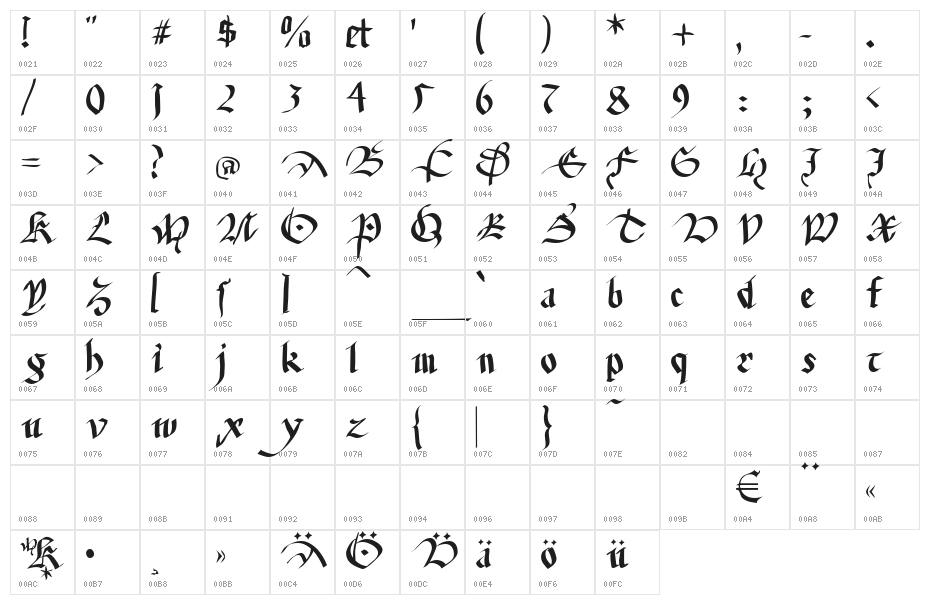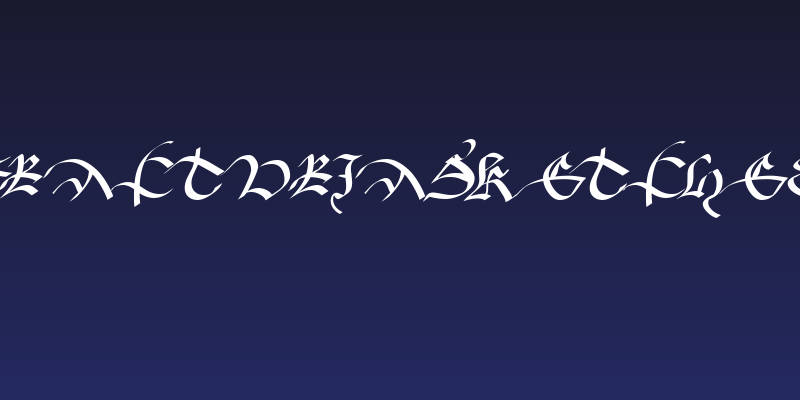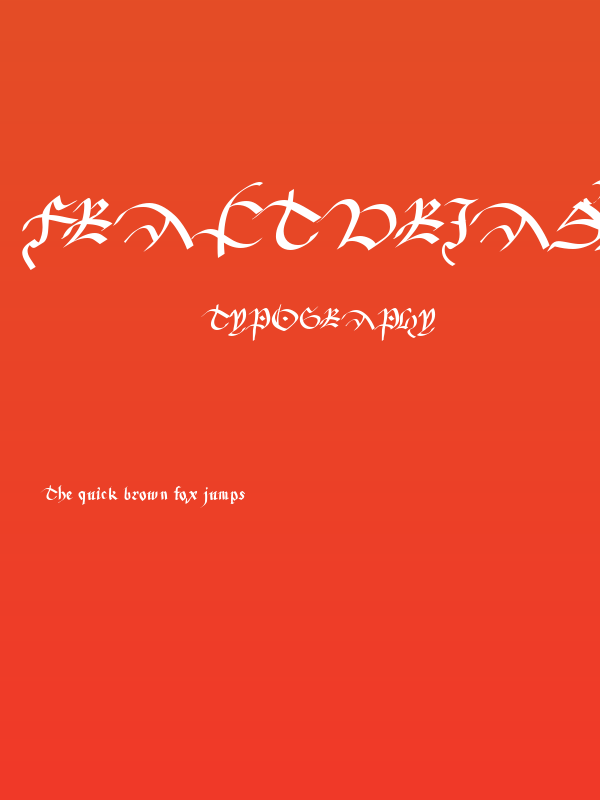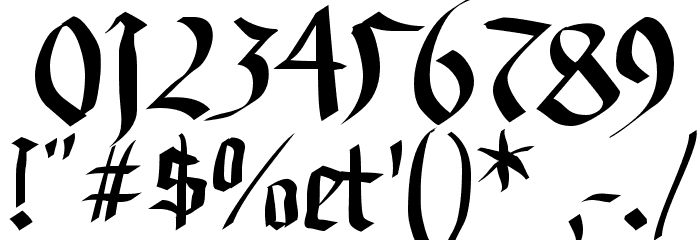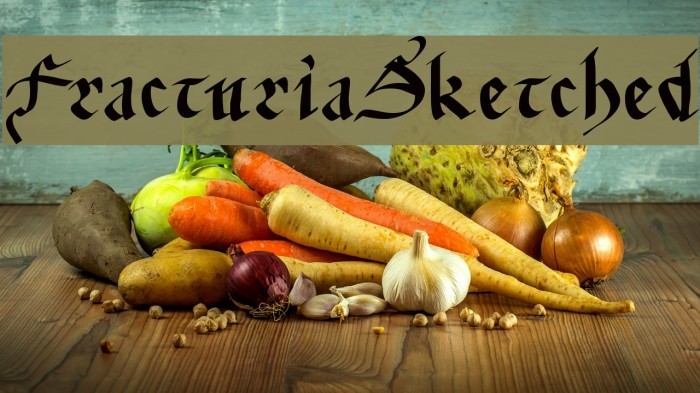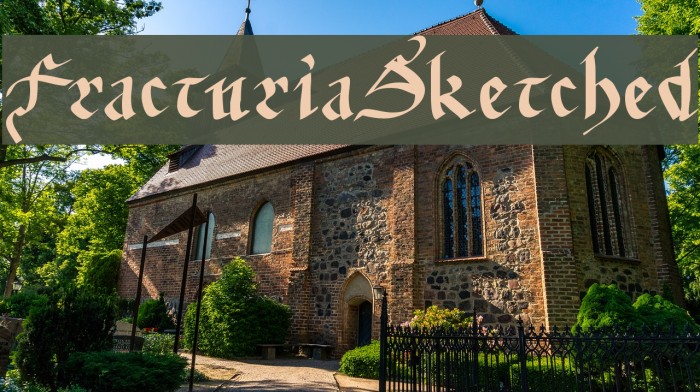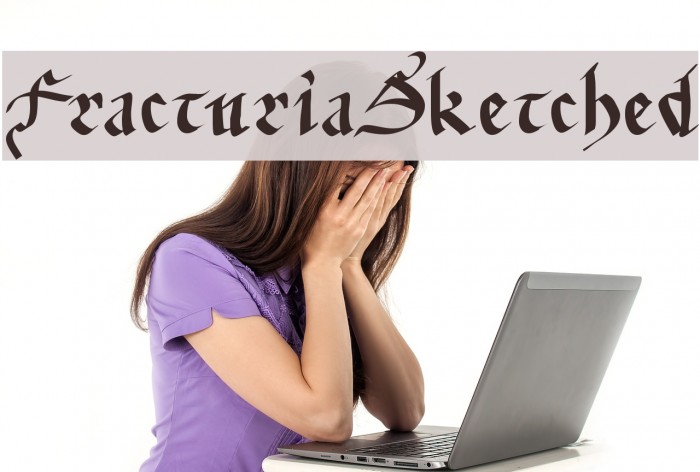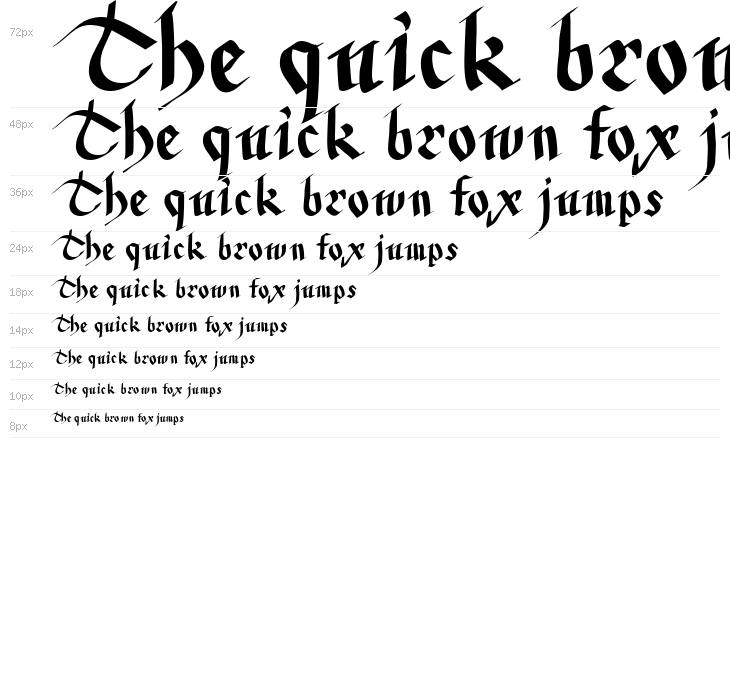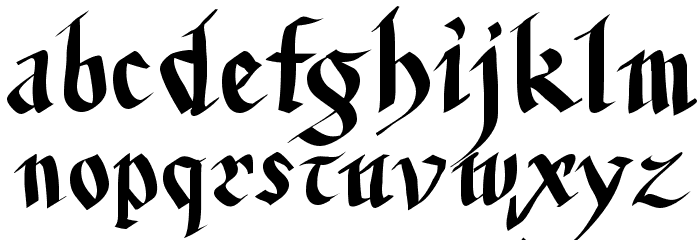
FracturiaSketched Font
| Progetti proposti | Suitable for projects that require a historical or gothic aesthetic, such as book covers, posters, or branding for vintage-themed products. |